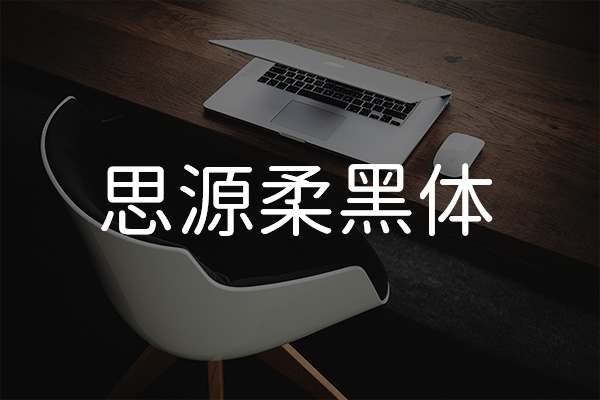
思源柔黑体
思源柔黑体(Gen Jyuu Gothic),这款优雅而富有活力的字体,源自于日本的一家字体工房,他们基于Google的开源字体“思源黑体”进行了修改和衍生。支持简体中文、繁体中文和日文三种语言,无论是简体还是繁体,你都能在这款字体中找到你需要的字符。由于字体开源并且无版权,你可以在商业用途中自由使用,而不用担心任何版权问题。
思源柔黑体与“圆体”有些相似,但它更加可爱、年轻有活力。这种字体的设计优雅,边角进行了圆角化处理,使得整个字体看起来更加柔和、流畅。无论是在设计、PPT制作、海报设计、Logo设计等各类场景中,思源柔黑体都能为你带来很好的视觉效果。
思源柔黑体一共发布了3个版本,标准版、L、X,它们的区别在于圆角的圆润程度不同。L版本的圆角最小,最尖;X版本的圆角最大,最圆;而标准版则是介于两者之间。每个版本都有7种字重,以及3种字形样式(包括等宽字体),你可以根据自己的喜好选择使用。
思源柔黑体效果预览